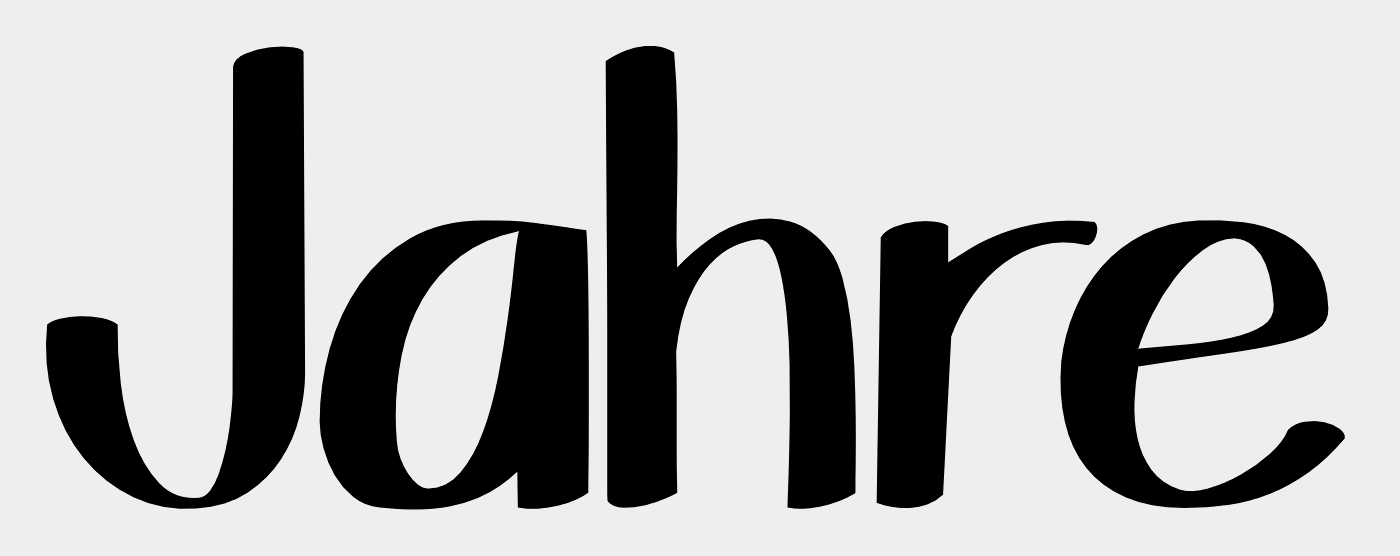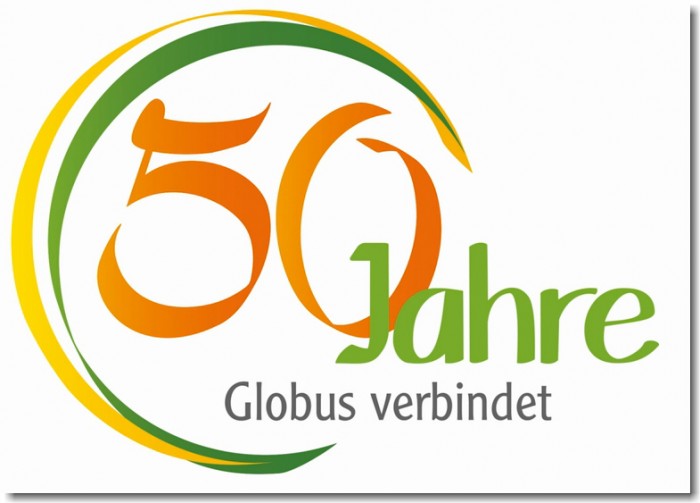
welche Schriftart könnte "50 Jahre" sein?
Es könnten auch zwei verschiedene sein "50" und "Jahre"
Ich könnte den Schriftzug natürlich nachzeichnen, brauche aber "110".
Die 50 scheint mir handgemacht, da stimmen Richtung und Neigung des Pinsels überhaupt nicht überein.
"ahre" stimmt, das "J" ist wohl auch selbstgemacht.
Gibt es für "50" etwas ähnliches? Nach welchen Begriffen muss ich suchen?
Ich würde mal nach Script / Brush schauen … evtl passt so was als Grundlage?